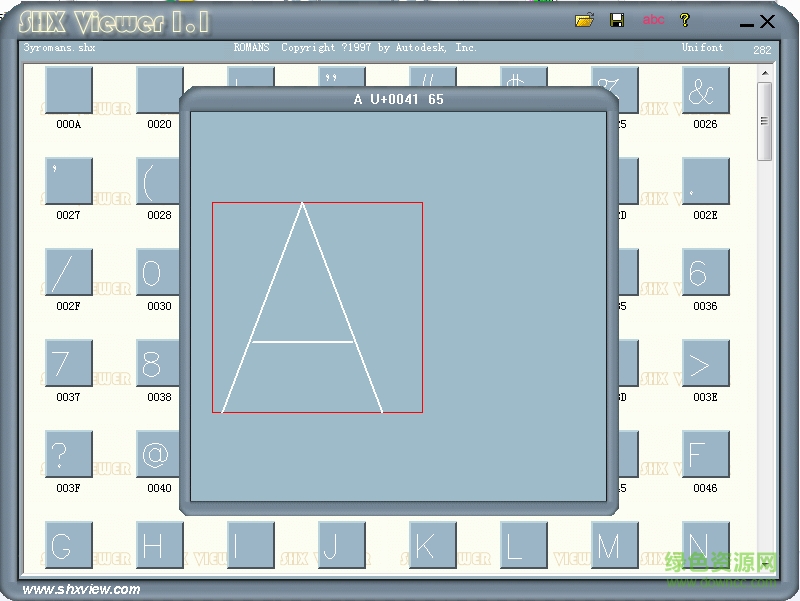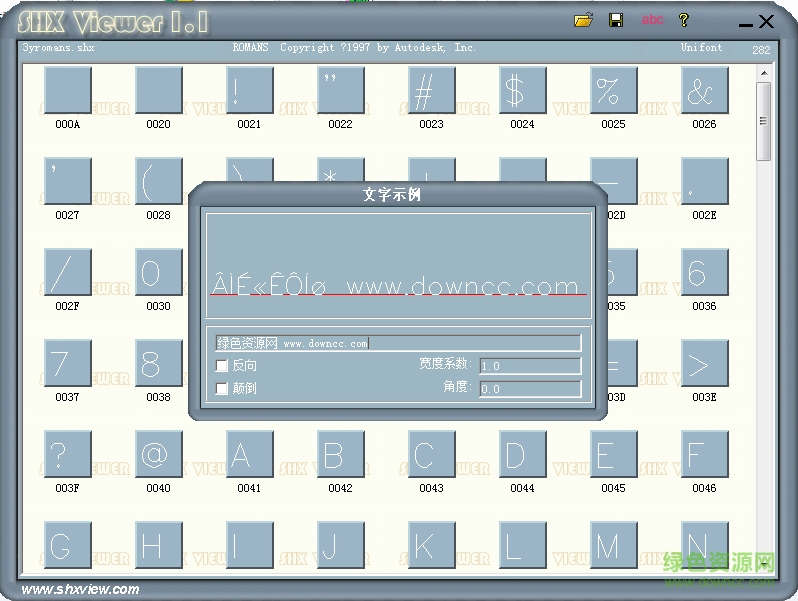
3yromans.shx是一款unifont字體,是autocad中的常規(guī)字體,擁有282個(gè)字符,包括數(shù)字、字母、希臘數(shù)字符號(hào)等,若你有符號(hào)設(shè)計(jì)上的需要,不妨來(lái)綠色資源網(wǎng)免費(fèi)下載體驗(yàn)!
3yromans.shx即romans.shx字體,擁有較多的符號(hào)的數(shù)字,支持?jǐn)?shù)學(xué)類符號(hào)的編輯和數(shù)字英文的書(shū)寫,不支持中文輸入,可適用于廣告創(chuàng)意、尺寸標(biāo)準(zhǔn)、排版編輯等領(lǐng)域。